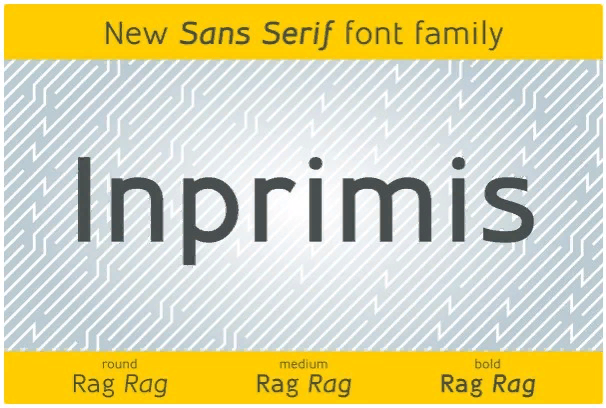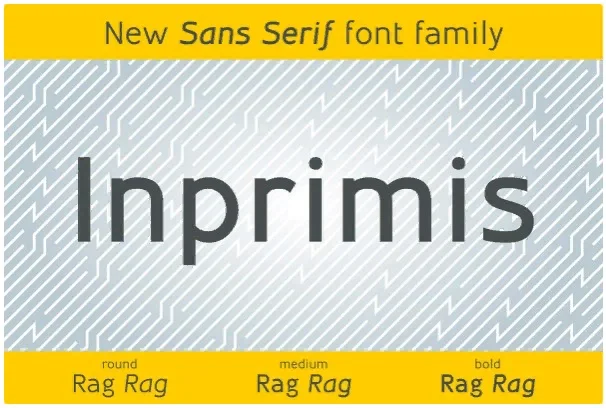
[Creativemarket] Inprimis Font (2021)
Inprimis
- это новое семейство шрифтов sans serif, основанное на типографике "старого стиля", переведенной в эпоху moder. Смесь геометрических форм, старинной вязи и забытых (или забытых?) глифов.
Выпускается в 6 стилях: 3 вертикальных и 3 курсивных.
Каждый стиль включает расширенную языковую поддержку, лигатуры и многое другое.
¶ 490 глифов в каждом варианте (всего 2940)
¶ Стандартный + произвольная лигатура
¶ Альтернативный набор стилей
¶ Малая прописная
¶ Латинский расширенный
¶ Подстрочный + старый стиль фигурный линейный или табличный
¶ Числитель + Знаменатель + Подстрочный индекс + Надстрочный индекс
Сейчас семейство Inprimis находится в версии 1.26 и дополнено этими вариантами:
55 Обычный
56 Курсив
65 Средний
66 Средний курсив
75 Жирный
76 Полужирный курсив
Работа продолжается:
45 светлый
46 светлый курсив
85 чёрный
86 черный курсив
Inprimis невероятно полезен в большинстве творческих областей, таких как журнал, плакат, книга, композиция.